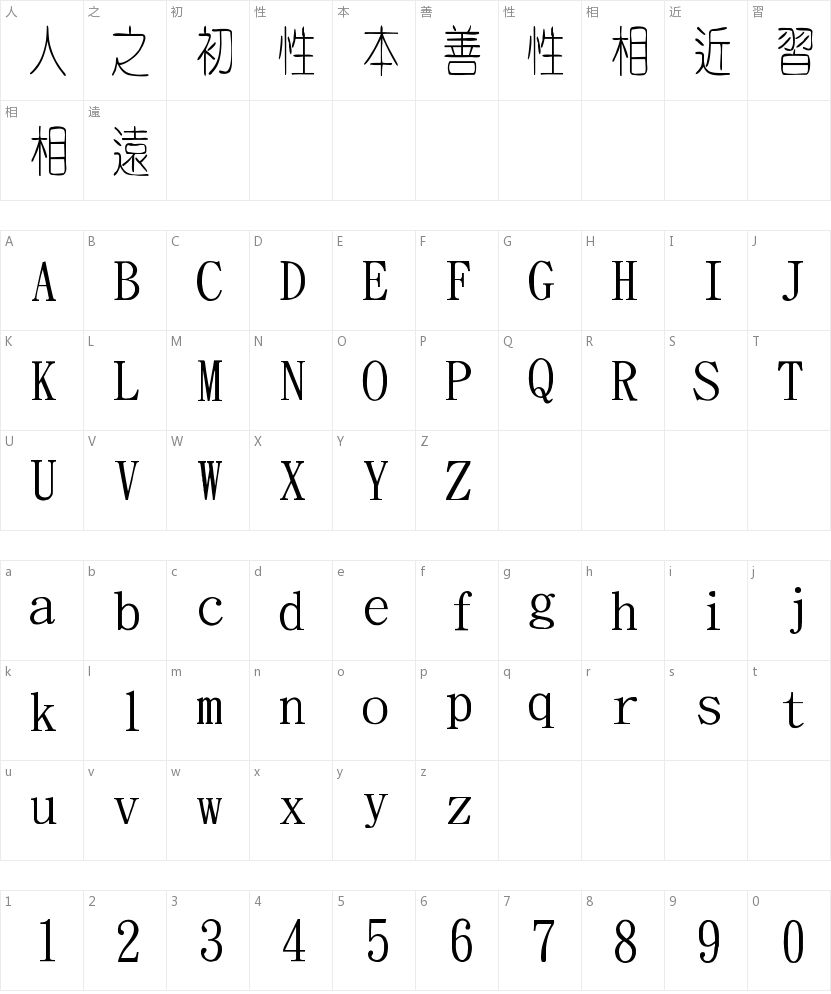
金梅细圆原体国际码
金梅细圆原体国际码(Jinmei Xiyuan International Code)是一种针对中文字符的编码标准,是由中国计算机学会(CCS)组织制定的,用于字符编码的国际标准,主要针对中文字符。它是一种基于Unicode的国际码,它的编码格式为UTF-8,支持中文简体、繁体、日文、英文、韩文等多种语言。金梅细圆原体国际码字体(Jinmei Xiyuan International Code Font)是一款支持金梅细圆原体国际码的字体,它可以支持中文简体、繁体、日文、英文、韩文等多种语言,是一款非常实用的字体。
金梅细圆原体国际码是一款非常不错的手写艺术字体,具有很好的视觉感,适合于文化类的宣传设计、商业类品牌的广告和产品包装设计以及个性化文字排版等较多场景。